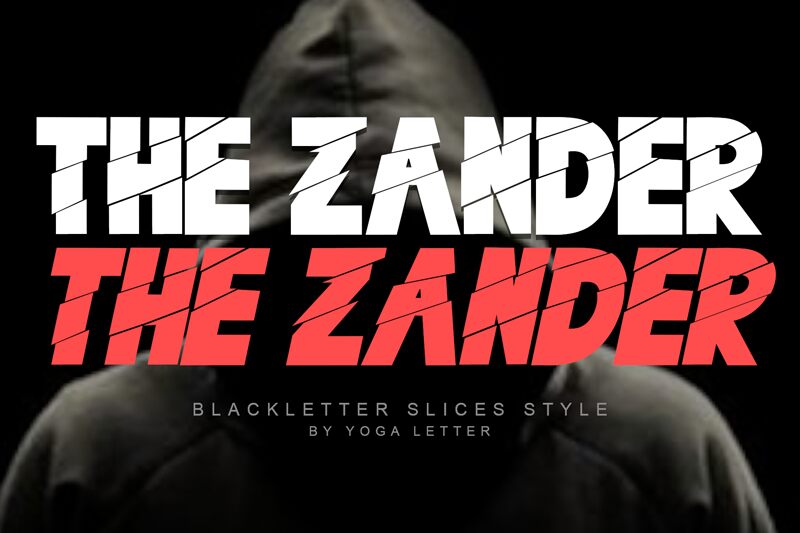
Písmo Zander od Yoga Letter je bezplatný, zkreslený displejový font s masivními, geometrickými písmeny, která jsou protnuta ostrými diagonálními řezy. Jeho zaoblené tvary a tvrdé seky dodávají abecedě roztříštěný, plakátový rytmus, který je jako stvořený pro výraznou grafiku.
Zander skvěle funguje na koncertních plakátech, herních titulech, sportovní grafice, brandingu streetwearu a výrazných bannerech na sociálních sítích, protože jeho „nařezaná“ struktura v sobě nese jasný pocit pohybu a napětí. Tento bezplatný font se také hodí pro loga a krátké redakční nadpisy, kdy hledáte písmo, které působí zubatě, stylizovaně a je navrženo pro maximální vizuální dopad.